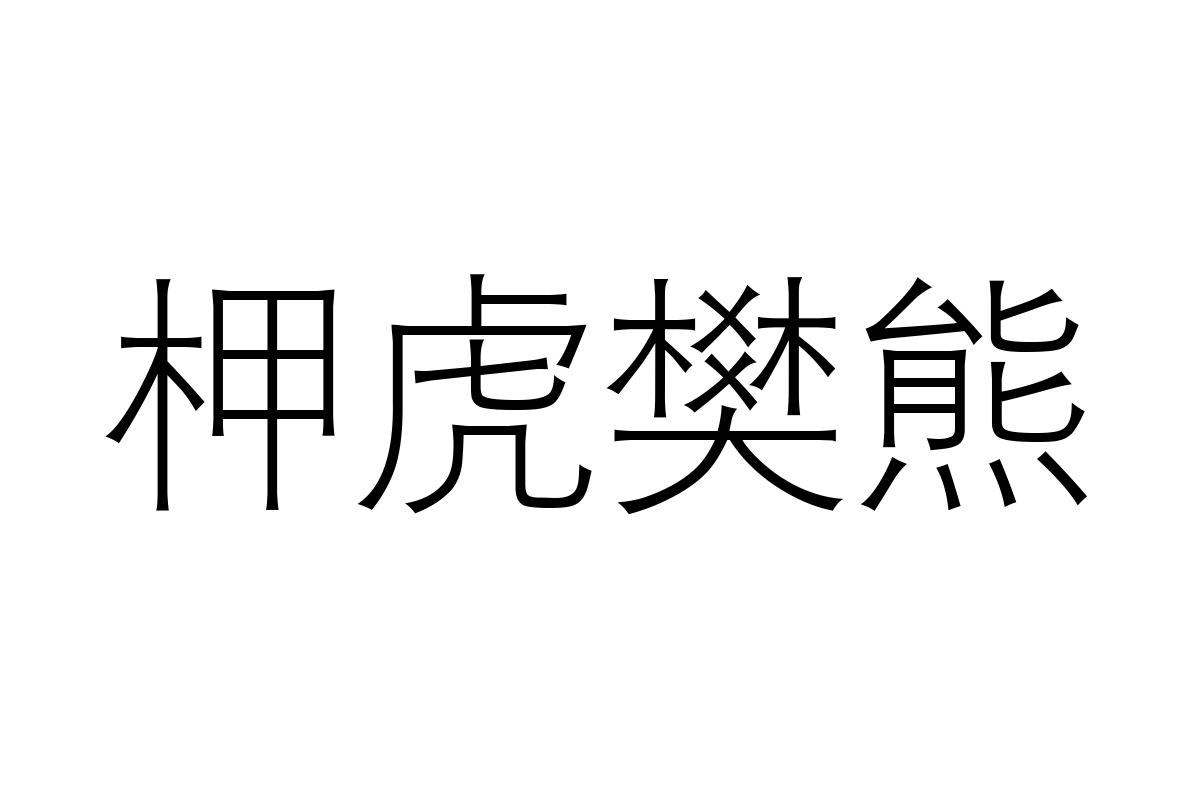
汉仪细等线是一款由汉仪公司推出的中文字体。这款字体的特点是笔画细腻,字形优美,线条流畅,适合用于需要精细文字的场合。它的设计灵感来源于传统书法,具有浓厚的东方韵味,给人一种古朴典雅的感觉。
汉仪细等线的特点如下:
1. 笔画细腻:汉仪细等线的笔画线条流畅,细节处理得当,使得文字看起来更加精致和美观。
2. 字形优美:汉仪细等线的字形设计独特,线条流畅,给人一种优美的视觉享受。
3. 风格古典:汉仪细等线的设计灵感来源于传统书法,具有浓厚的东方韵味,适合用于需要展示传统文化特色的场合。
4. 适用范围广泛:汉仪细等线适用于各种需要精细文字的场合,如广告、书籍、杂志、网站等。
总之,汉仪细等线是一款非常优秀的中文字体,无论是在设计还是在实际使用中都能给人留下深刻的印象。